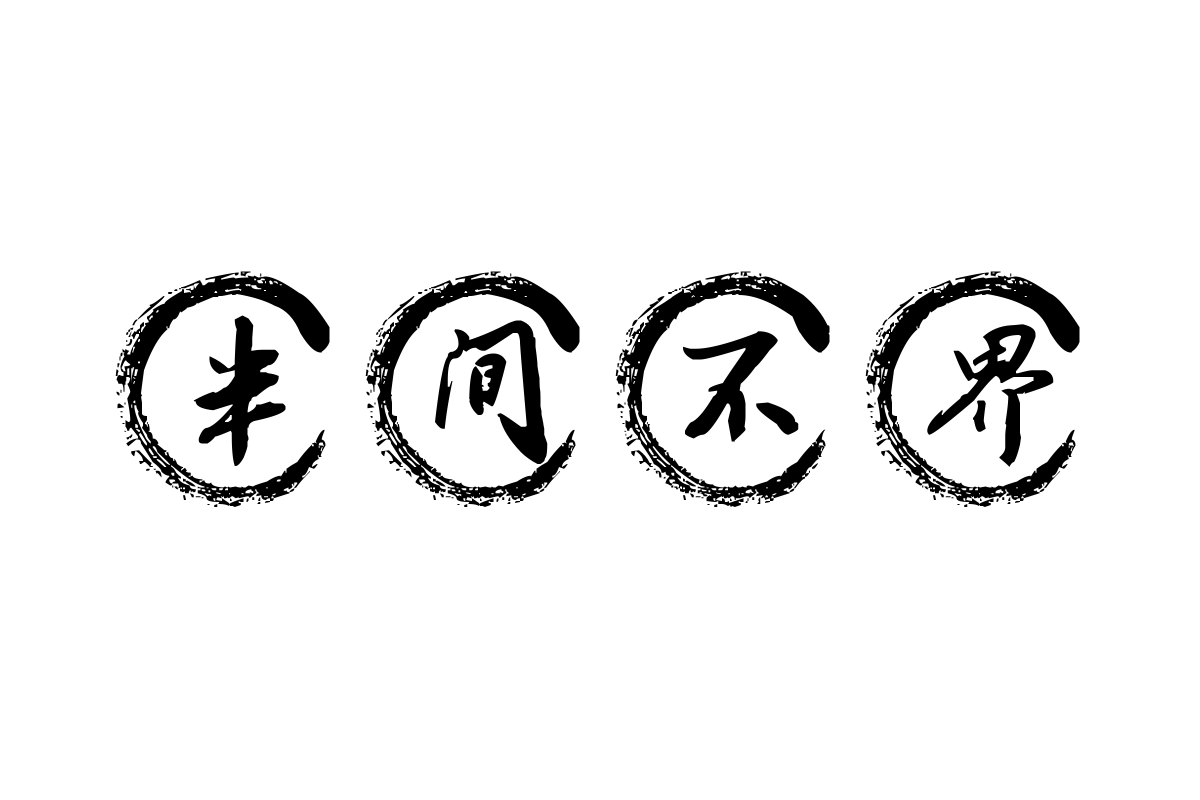
汉呈水墨中国风字体是一种具有浓郁中国传统风格和文化底蕴的字体。它采用了独特的书法艺术元素,将汉字的笔画、结构、形态等进行了创新和变化,形成了一种独特的视觉效果。
这种字体的特点是线条流畅,富有弹性和动感,既有古典的韵味,又不失现代感。它的笔画粗细不一,既有粗犷豪放的气势,又有细腻婉约的美感。同时,它还注重字与字之间的间距和平衡,使得整体布局显得和谐而统一。
汉呈水墨中国风字体适用于各种需要展现中国传统文化特色的场合,如书法作品、广告设计、包装印刷、书籍装帧等。它不仅能够提升作品的文化内涵和审美价值,还能够增强人们对中国传统文化的认同感和自豪感。